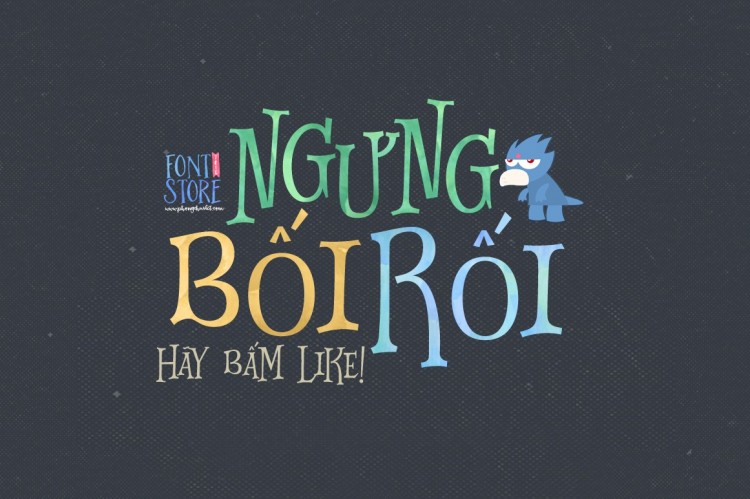
Font việt hóa FS Endless Sorrow (2 font)
Giới thiệu về bộ Font việt hóa FS Endless Sorrow (2 font)
Trong thế giới đồ họa hiện đại, việc tìm kiếm một Font Miễn Phí có cá tính riêng biệt là điều vô cùng quan trọng đối với các nhà thiết kế. Font việt hóa FS Endless Sorrow (2 font) là một bộ phông chữ độc đáo, mang đậm phong cách thủ công đầy cảm xúc. Được lấy cảm hứng từ những nét vẽ tay mộc mạc, bộ font này gợi lên vẻ đẹp cổ điển, pha chút hoài niệm và bí ẩn. Với hai định dạng khác nhau trong cùng một bộ, người dùng có thể linh hoạt thay đổi để tạo nên sự đa dạng cho các tác phẩm nghệ thuật của mình.
Đặc điểm nổi bật của bộ Font việt hóa FS Endless Sorrow (2 font)
Phong cách thiết kế thủ công ấn tượng
Bộ Font việt hóa FS Endless Sorrow (2 font) sở hữu những đường nét không hoàn hảo một cách cố ý, tạo cảm giác gần gũi và chân thực. Đây là lựa chọn tuyệt vời cho các dự án thiết kế bìa sách, áp phích phim hoặc các nội dung mang tính kể chuyện. Sự kết hợp giữa các nét thanh nét đậm không theo quy tắc cứng nhắc giúp phông chữ này trở nên nổi bật trên mọi nền chất liệu.
Khả năng ứng dụng đa dạng trong giáo dục và đời sống
Không chỉ dành cho dân chuyên nghiệp, bộ font này còn rất phù hợp để các bạn học sinh dùng trang trí báo tường hoặc làm slide thuyết trình sinh động. Nhờ quy trình việt hóa chỉn chu, các dấu câu tiếng Việt được đặt vị trí hợp lý, đảm bảo tính thẩm mỹ cao nhất khi soạn thảo văn bản dài hoặc tiêu đề ngắn.